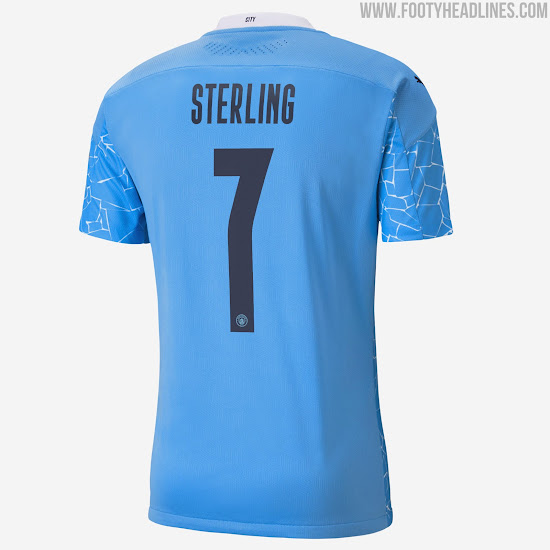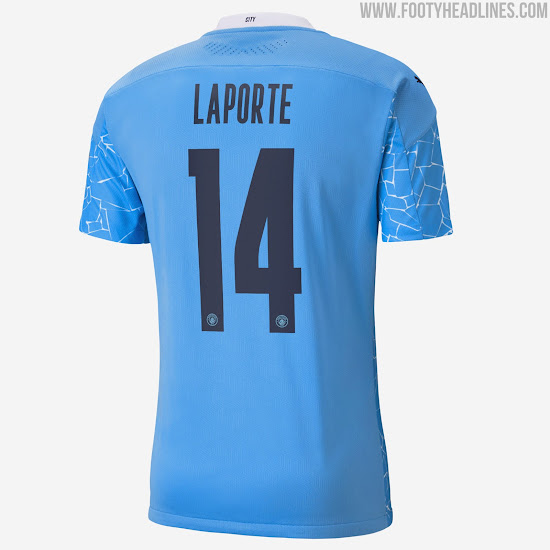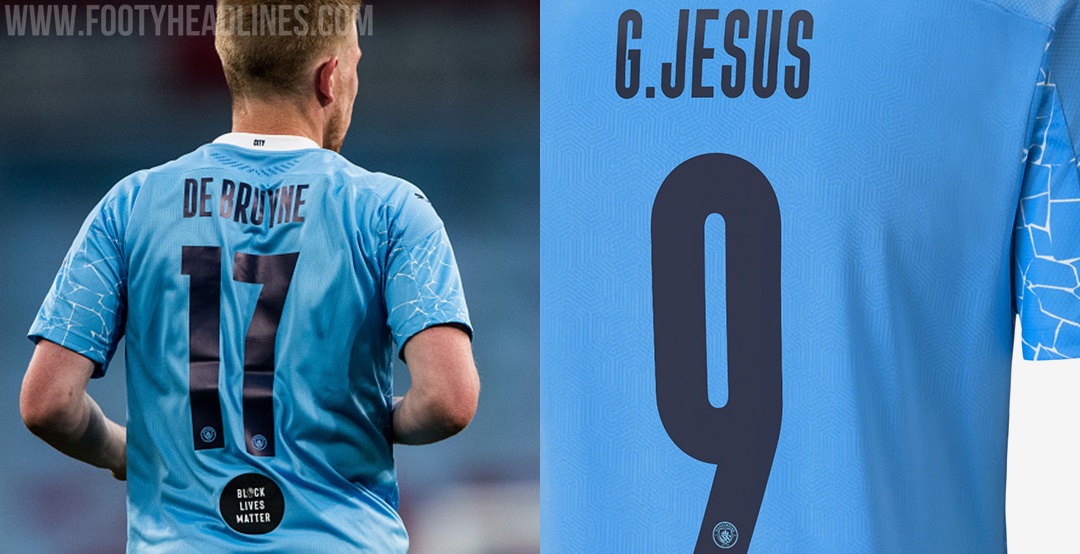
Manchester City 20-21 Pokal-Schriftart veröffentlicht - Globaler Puma-Stil
Wie in den vergangenen Spielzeiten erhielt Manchester City auch in den Pokalspielen 2020/21 eine besondere Schriftart. Wir werfen einen genaueren Blick auf die Manchester City 20-21 Pokal-Schriftart, die am Samstag im FA-Cup-Halbfinale gegen Arsenal Premiere feierte.
Puma Manchester City 20-21 Schriftart
Der Stil, der für die Manchester City 20-21 Pokal-Schriftart verwendet wird, hat einen schmalen und länglichen Auftritt. Es weist das Man City Wappen am unteren Ende auf, während die Nummern und Buchstaben dunkelblau ohne einen Grafikeffekt sind.
Tatsächlich wurde die Man City 20-21 Schriftart nicht für den Club entworfen, sondern entspricht der standardmäßigen Puma 2020 Trikot-Schriftart.
Manchester City 2019-20 Trikot-Schriftart
Die neue Schriftart wird von Manchester City in allen Pokalwettbewerben (Champions League, FA Cup, League Cup) für die Saison 2020/2021 verwendet werden.
Premier League Schriftart